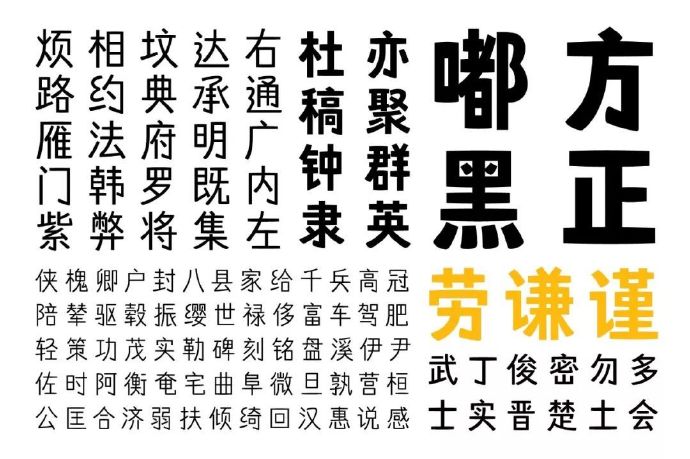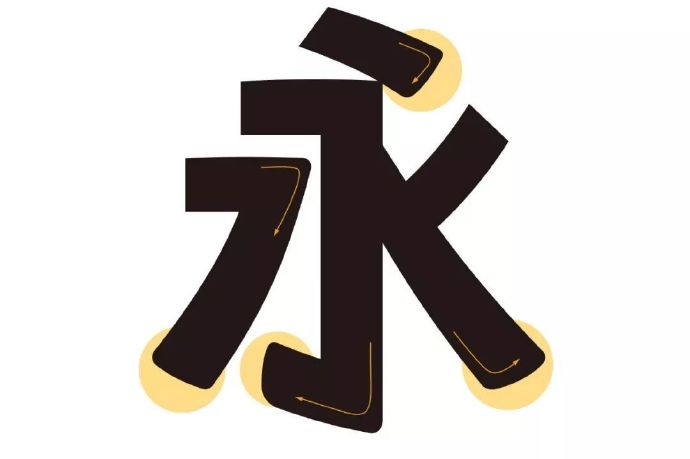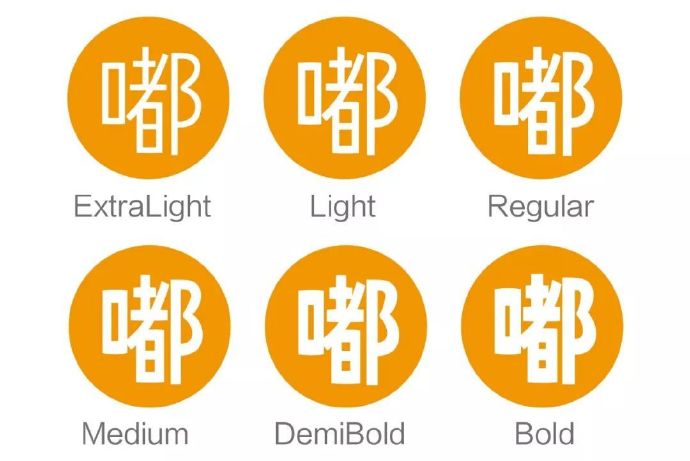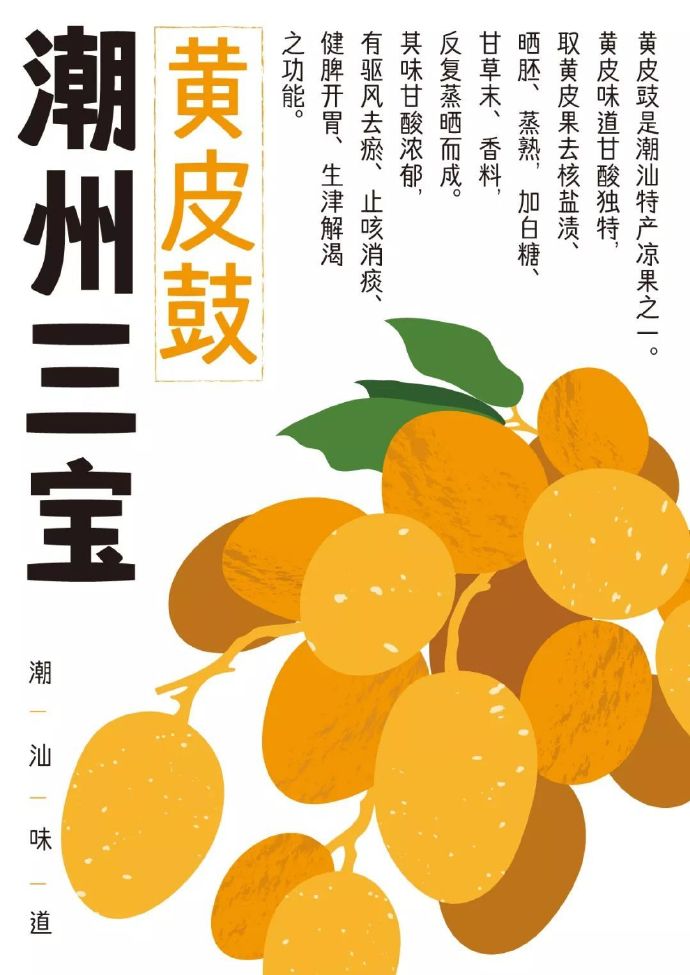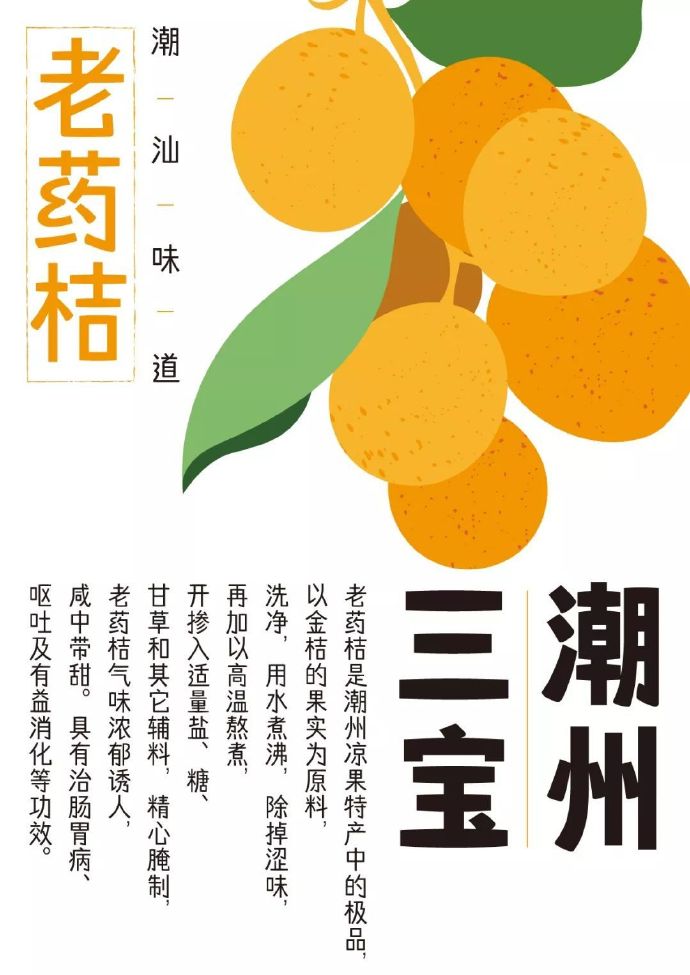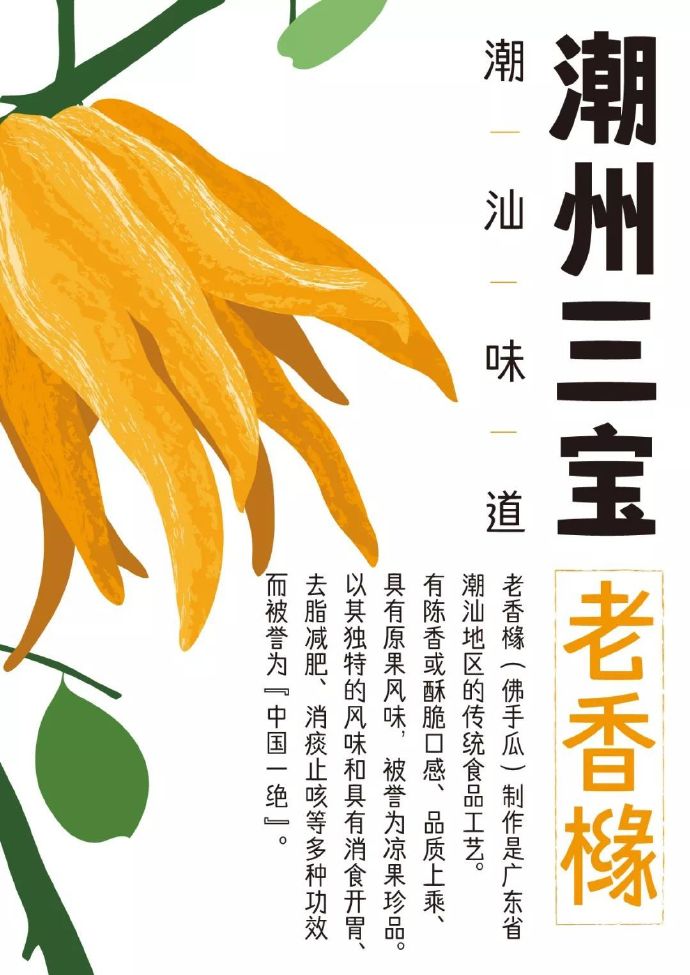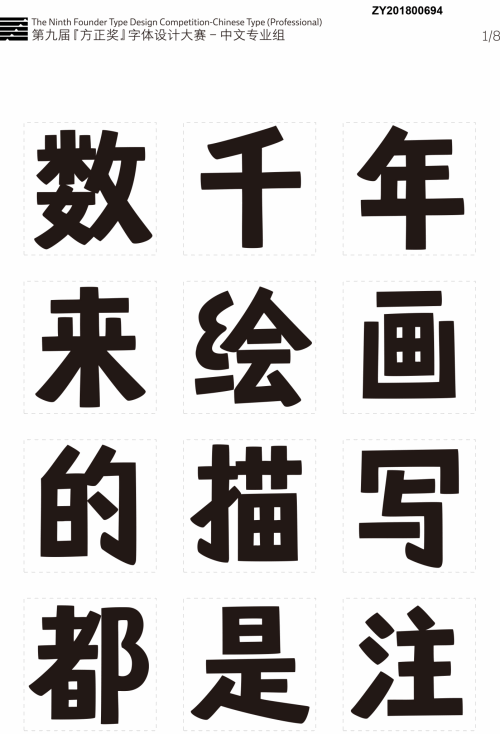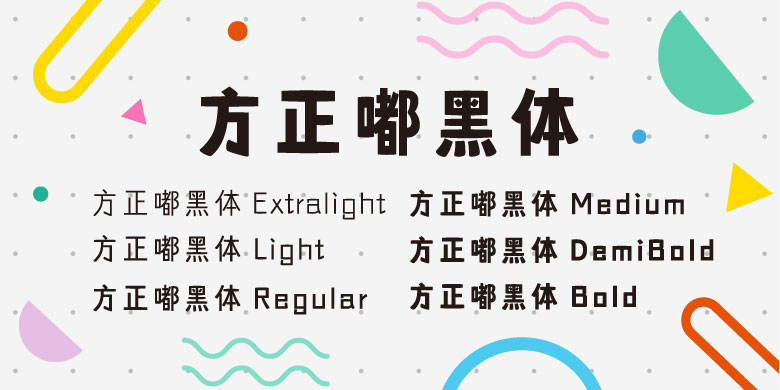
方正嘟黑家族
字体品牌: 方正字库 设计师: 顾正友 字体分类: 创意字体 字体属性: 精品字 字符集: 大陆简体(GB2312-80) 发布时间: 2019
作者顾正友:方正字库签约设计师、深圳市平面设计协会会员、重庆工商大学现代国际设计艺术学院客座教授。方正嘟黑在黑体笔形基础上融入了楷书的笔意,具有书写感。字体线条刚柔并济,稚拙而有生活气息